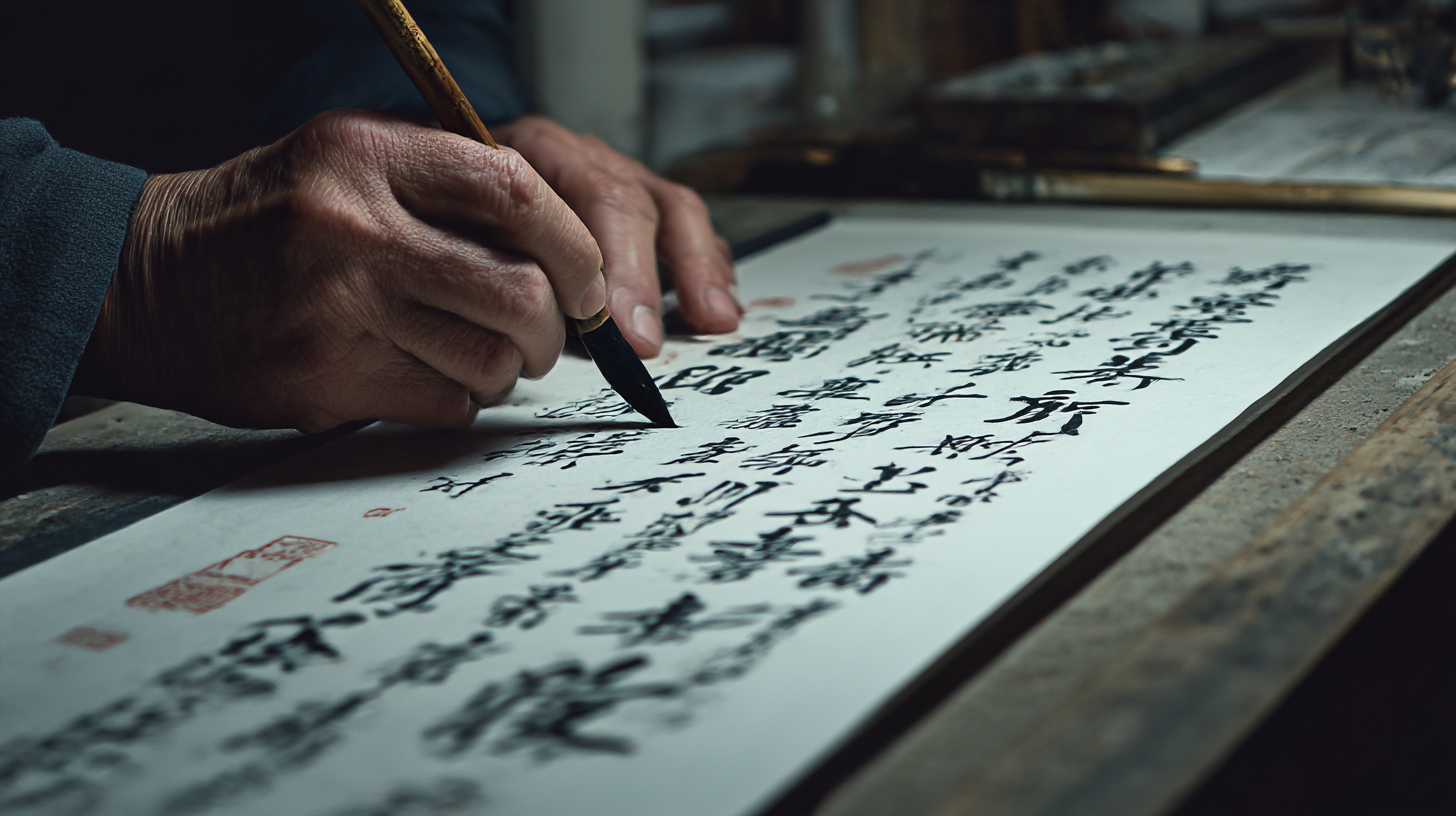
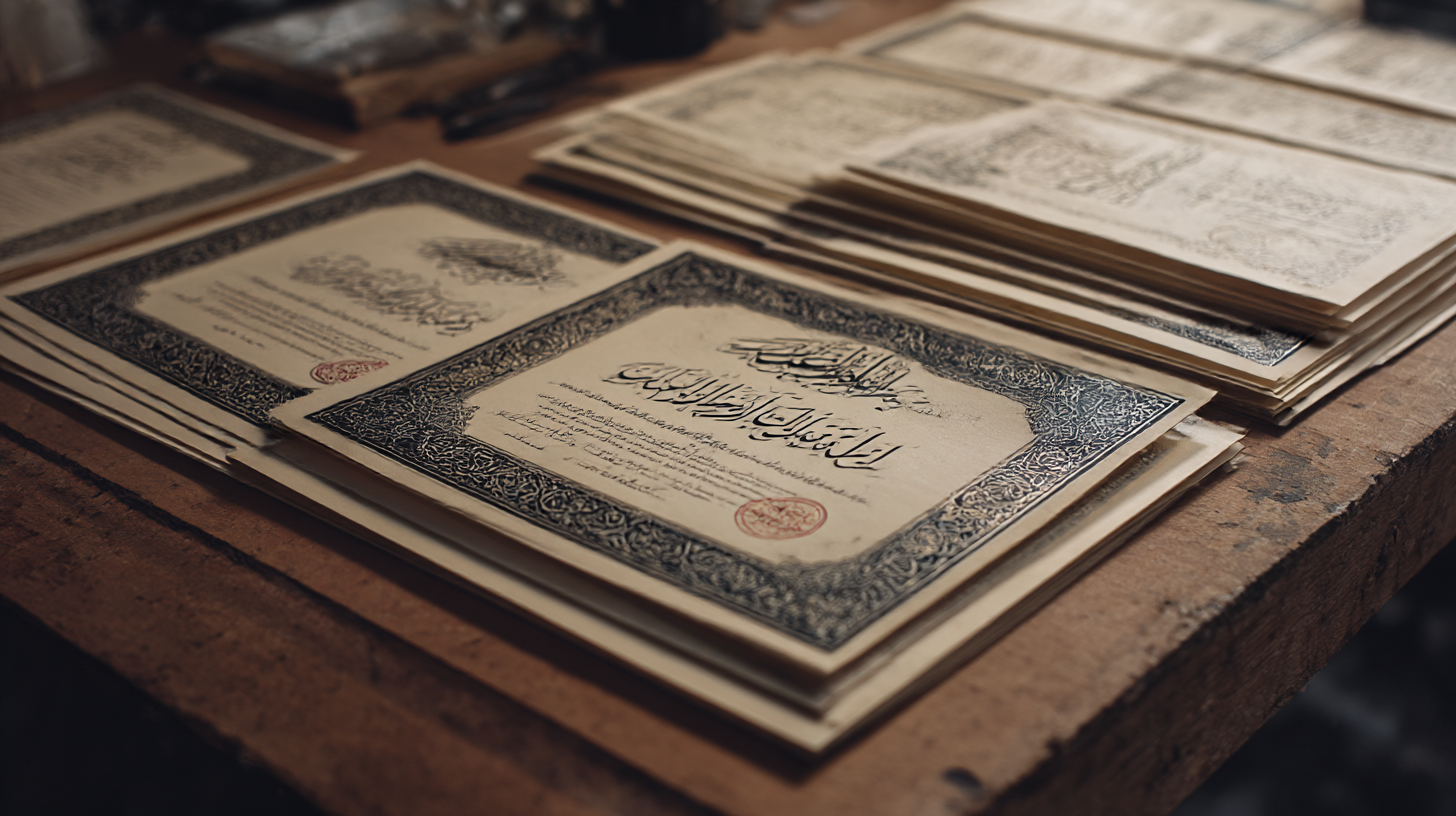
캘리그라피 자격증, 부업으로 연결되는 길 캘리그라피는 손글씨에 감성을 입히는 예술로, 단순한 취미에서 부업으로 연결될 수 있는 매력적인 분야예요. 예쁜 글씨체만 익히면 되는 게 아니라 감정과 메시지를 담아내는 표현력도 중요하죠.
이제는 캘리그라피 자격증을 통해 전문성을 인증받고, 그 실력을 바탕으로 다양한 활동을 펼칠 수 있어요. 저는 이 글을 통해 캘리그라피가 단순한 '글씨'를 넘어서 삶의 기회를 열어주는 열쇠가 될 수 있다는 걸 소개해보려고 해요.
🖌 캘리그라피란 무엇일까?
캘리그라피는 단순히 글씨를 예쁘게 쓰는 것이 아니에요. 감정을 담은 손글씨를 통해 사람의 마음을 움직이는 예술이랍니다. 손끝으로 전해지는 감정과 메시지는 활자나 디지털 폰트로는 느낄 수 없는 깊은 울림을 줘요. 특히 요즘처럼 감성이 중요한 시대엔 손글씨 하나로 감동을 줄 수 있답니다.
전통적인 서예와는 달리 캘리그라피는 자유롭고 창의적인 표현을 중요시해요. 굵기, 간격, 흐름 등 글씨의 형태를 통해 감정을 전달할 수 있기 때문에 아트워크로도 높은 평가를 받고 있어요. 특히 한국에서는 한글의 곡선미가 돋보이는 작품들이 인기를 끌고 있어요.
디지털 시대에도 캘리그라피는 꾸준히 주목받고 있어요. 감성적인 광고 문구나 SNS 콘텐츠에 자주 활용되며, 개성 있는 브랜드 아이덴티티를 만드는 데도 필수적인 요소로 자리 잡고 있어요. 손글씨 특유의 인간적인 매력이 사람들에게 따뜻함을 전달해주기 때문이에요.
요즘은 캘리그라피를 단순한 취미를 넘어서 직업으로 삼는 사람들도 많아졌어요. 결혼식 청첩장, 기업 광고, 유튜브 썸네일, 카페 메뉴판 등 다양한 분야에서 캘리그라퍼의 손길이 필요하답니다. 이처럼 수요가 점점 확대되면서 자격증을 취득해 전문성을 갖추려는 사람들이 늘고 있어요.
🖋 캘리그라피 스타일 비교표
스타일 특징 적용 예시 모던 캘리 자유로운 구조, 부드러운 곡선 SNS 게시물, 엽서 클래식 캘리 정형화된 서체, 균형감 강조 공식 문서, 전시 작품 일러스트 캘리 그림과 함께 감성 표현 굿즈, 캘린더 디자인 붓글씨 캘리 붓 특유의 강약 조절 전통 행사, 예술 전시 내가 생각했을 때 캘리그라피는 내면의 감성을 밖으로 표현하는 가장 따뜻한 방식 중 하나인 것 같아요. 글씨 하나하나에 마음이 실리기 때문에 보는 사람도 자연스럽게 공감하게 되거든요. 그리고 이게 바로 캘리그라피의 진짜 매력이 아닐까 싶어요. 😊
📚 자격증 종류와 취득 과정
캘리그라피 자격증은 다양한 기관에서 발급하고 있어요. 가장 많이 알려진 자격증은 '한국캘리그라피디자인협회', '한국실용글씨협회' 등의 민간자격증이랍니다. 이 자격증들은 공인된 국가자격은 아니지만, 실무 현장에서는 널리 인정받고 있어요. 실력을 기반으로 검정에 응시할 수 있고, 창작 능력도 함께 평가돼요.
보통 2급부터 시작해서 1급, 강사 자격까지 단계적으로 올라갈 수 있어요. 2급은 비교적 진입 장벽이 낮기 때문에 초보자도 부담 없이 도전할 수 있어요. 자격증 취득을 위해선 일정 기간 교육을 이수한 후, 실기 및 이론 시험에 통과해야 해요. 시험은 직접 글씨를 쓰는 방식으로 진행되며, 디자인 구성력도 중요한 요소랍니다.
자격증 교육 과정은 보통 온라인 강의나 오프라인 학원에서 받을 수 있어요. 특히 요즘은 온라인으로도 충분히 실력을 키울 수 있어서 직장인이나 육아 중인 분들에게도 접근성이 좋아요. 실시간 피드백이 가능한 커뮤니티도 많아서 피드백을 통해 빠르게 실력이 느는 경우도 많답니다.
자격증을 따면 끝이 아니라 시작이에요. 이후에는 포트폴리오를 준비하고 실제 작업 의뢰를 받아보는 경험이 중요해요. 자격증은 실력을 보여주는 수단이지만, 진짜 경쟁력은 '나만의 스타일'을 얼마나 잘 표현하느냐에 달려 있어요. 자격증은 실력을 증명하는 '티켓'일 뿐, 결국 실전 경험이 실력을 탄탄하게 만들어줘요.
📄 자격증 종류 비교표
자격증명 발급 기관 자격 구분 취득 난이도 특징 캘리그라피 2급 한국캘리그라피디자인협회 민간자격 ★★☆☆☆ 초보자용, 입문 단계 캘리그라피 1급 한국실용글씨협회 민간자격 ★★★☆☆ 실무 활용 능력 요구 캘리그라피 강사 자격 한국캘리그라피교육원 민간자격 ★★★★☆ 교육 강의 가능 캘리그라피 마스터 디자인연합협회 민간자격 ★★★★★ 작품 창작 및 심사 가능 위 자격증 중 어떤 걸 선택하느냐는 본인의 목적에 따라 달라져요. 취미로 즐기고 싶다면 2급이나 1급 정도가 적당하고, 교육이나 강사 활동을 고려한다면 강사 자격 이상을 목표로 하는 게 좋아요. 강의를 하고 싶은 분은 해당 교육기관의 커리큘럼을 꼼꼼히 비교해보는 게 중요해요.
💼 취미에서 부업으로 발전하기
캘리그라피는 단순히 여가 시간을 보내는 취미로 시작되기 쉽지만, 조금만 방향을 바꾸면 부업으로 연결되기 딱 좋아요. 내가 만든 손글씨 작품을 누군가가 돈 주고 구매한다는 건 정말 뿌듯한 일이죠. 무엇보다 온라인 플랫폼 덕분에 누구나 작품을 세상에 보여줄 수 있게 되었어요.
요즘은 SNS만 잘 운영해도 캘리그라피로 수익을 낼 수 있는 기회가 많아졌어요. 인스타그램, 블로그, 유튜브, 스마트스토어 등을 통해 작품을 판매하거나 강의를 열 수 있답니다. 자신만의 개성이 담긴 글씨와 표현 방식으로 팔로워들의 공감을 얻으면 브랜드 협찬이나 주문 의뢰도 자연스럽게 들어오게 돼요.
특히 수공예 마켓이나 온라인 클래스를 통해 상품을 판매하면 부업으로 꽤 괜찮은 수입을 만들 수 있어요. 청첩장 디자인, 감성 엽서, 포스터, 소품 제작 등 캘리그라피가 들어가는 상품은 무궁무진하거든요. 직접 굿즈를 만들어 판매하는 ‘작가 마켓’은 창작자에게 꿈같은 기회예요.
회사원, 주부, 프리랜서 누구든지 캘리그라피는 부업이 될 수 있어요. 하루에 1~2시간만 투자해도 실력을 쌓을 수 있고, 시간 제약 없이 운영할 수 있어서 본업과 병행하기에도 적합하답니다. 게다가 요즘은 ‘감성 소비’를 좋아하는 사람들이 많아서 손글씨만으로도 충분한 경쟁력이 생겨요.
💡 캘리그라피 부업 방법 비교표
부업 유형 특징 수익 구조 시작 난이도 굿즈 제작 판매 감성 제품으로 인기 제품 판매 수익 ★★★☆☆ 온라인 클래스 운영 꾸준한 수입 가능 강의 수강료 ★★★★☆ 청첩장/로고 제작 맞춤형 작업 의뢰비 수익 ★★★☆☆ SNS 콜라보 팔로워 수 기반 광고 협찬, 제휴 ★★☆☆☆ 캘리그라피는 정해진 형식이 없기 때문에 표현의 자유가 커요. 내가 어떤 문구를 어떤 스타일로 전달할지에 따라 전혀 다른 결과물이 나오니까 창의력이 발휘되는 부업이에요. 누구나 시작할 수 있지만, 내 감성을 담아내는 데 집중하면 진짜 '내 일'이 되는 순간이 찾아와요.
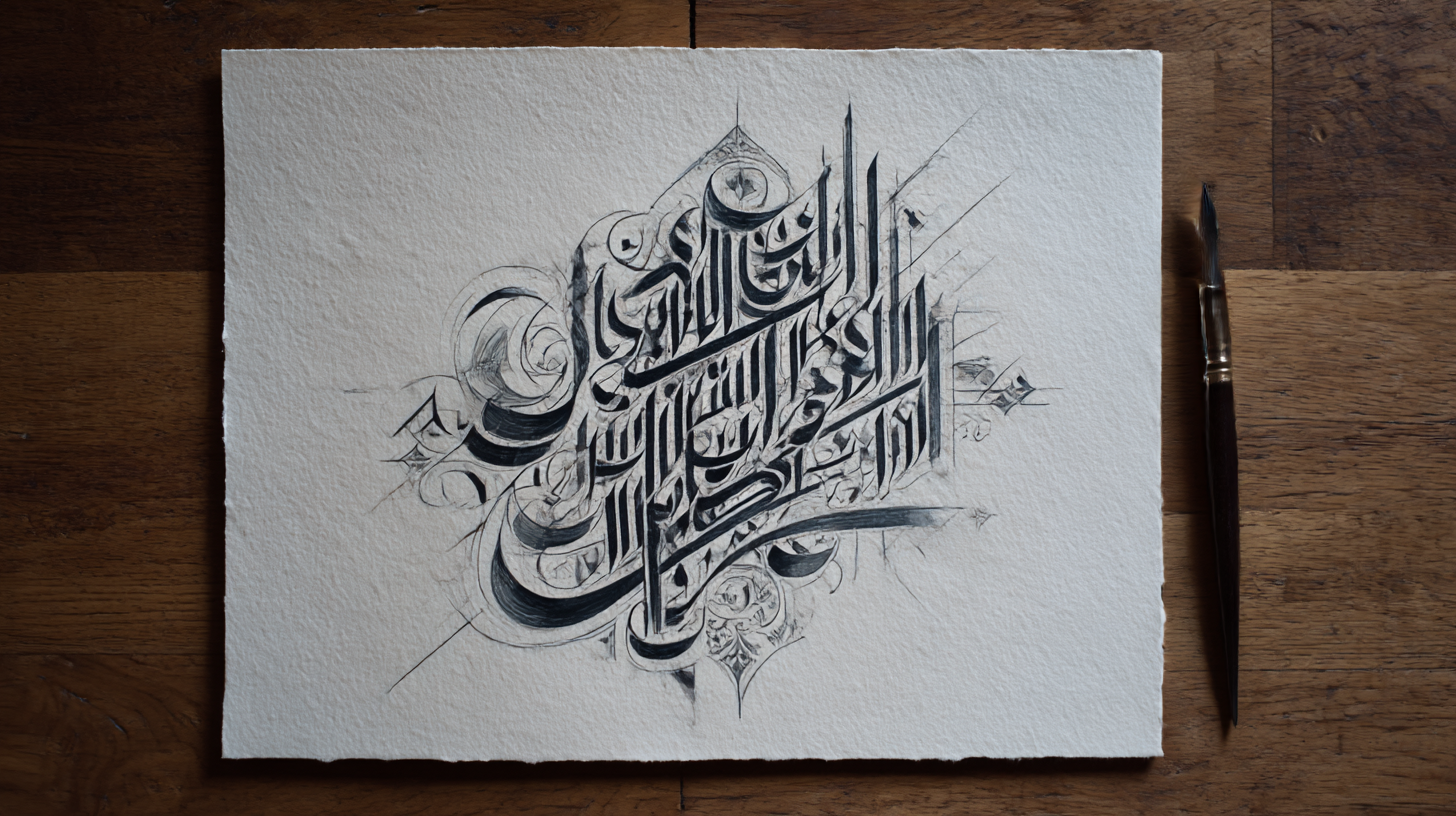
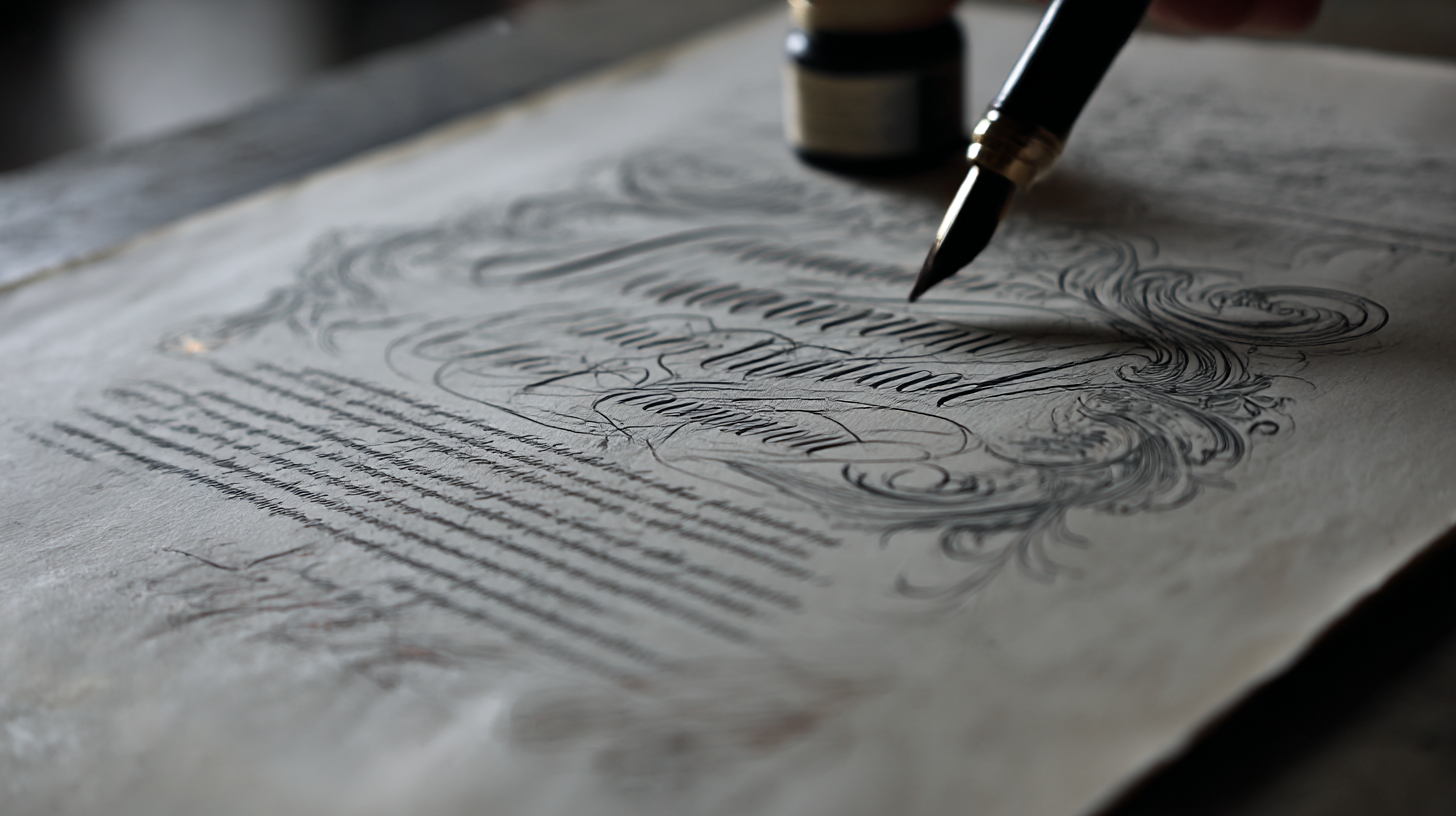
취미에서 부업으로 발전하기 💰 수익 창출 가능한 캘리그라피 분야
캘리그라피로 수익을 만들 수 있는 분야는 생각보다 훨씬 다양해요. 단순히 글씨 쓰는 활동을 넘어서 디자인과 콘텐츠가 결합된 영역이 많아졌기 때문이죠. 특히 '감성'이라는 키워드가 중요해진 요즘, 손글씨는 브랜드와 사람을 이어주는 중요한 매체로 주목받고 있어요.
첫 번째로 인기 있는 분야는 바로 ‘굿즈 제작’이에요. 손글씨로 만든 문구를 엽서, 포스터, 다이어리, 탁상달력 등에 적용해 판매하는 방식이죠. ‘오늘의 문장’, ‘마음 위로 엽서’ 같은 주제로 많은 사람들이 감동받고 구매해요. 공방이나 온라인 마켓, SNS를 통해 직접 판매할 수도 있어요.
두 번째는 ‘청첩장·감사카드 디자인’이에요. 결혼, 돌잔치, 개업 등 특별한 날을 기념하는 문구에 손글씨를 요청하는 사람들이 많아요. 정해진 글씨보다 개성 있고 따뜻한 느낌을 줄 수 있어서 많은 신랑신부, 행사 주최자들이 캘리그라피를 선택해요. 이 분야는 한 건당 단가가 높아 수익률이 좋아요.
세 번째는 ‘로고 및 브랜딩 디자인’이에요. 작은 브랜드, 카페, 독립서점 등에서는 감성적인 이미지를 위해 손글씨 로고를 선호하거든요. 특히 브랜딩 초기에 캘리그라피로 로고를 만든다면 따뜻한 이미지와 신뢰를 함께 줄 수 있어요. 실제로 유명 카페나 화장품 브랜드도 손글씨 로고를 활용해요.
📊 수익화 가능한 캘리그라피 분야 정리
분야 활동 예시 수익 유형 소요 시간 굿즈 제작 엽서, 달력, 포스터 판매 수익 중간 청첩장·카드 감사 인사, 초대장 주문 제작 수익 짧음 로고 디자인 브랜드 로고, 간판 디자인 수익 김 SNS 콘텐츠 감성 문구 이미지 협찬/광고 짧음 그 외에도 강연이나 워크숍, 기업 대상 출강, 클래스101 같은 온라인 플랫폼에서 수업을 열 수도 있어요. 잘 알려진 플랫폼에 입점하면 매달 정기 수입이 생기기도 해요. 이처럼 ‘감성’과 ‘글씨’가 중심이 되는 시장은 계속해서 확장 중이랍니다.
곧 이어질 섹션에서는 내 실력을 어떻게 사람들에게 보여줄 수 있을지, 효과적인 포트폴리오 제작과 SNS 운영법에 대해 알려줄게요. 이제 진짜 실전 감각을 키울 시간이에요! ✨
📷 포트폴리오와 SNS 활용법
캘리그라피를 부업으로 이어가려면, 내 실력을 효과적으로 보여줄 수 있는 '포트폴리오'가 필요해요. 단순히 잘 쓴 글씨를 나열하는 게 아니라, 나만의 스타일과 감성을 담아 사람들의 감정을 자극하는 것이 중요하죠. 시선을 사로잡는 작품 구성은 기본이에요.
좋은 포트폴리오란 단순히 사진 몇 장을 나열하는 게 아니에요. 예를 들어, "봄 감성 시리즈", "결혼 축하 문구", "카페 메뉴보드"처럼 주제별로 카테고리를 나눠 정리하면 훨씬 보기 좋아요. 작업 과정을 함께 보여주는 것도 신뢰감을 높이는 방법이에요. 손글씨가 완성되기까지의 흐름을 보여주면 보는 사람의 이해도도 높아져요.
Q4. 어떤 도구로 시작하는 게 좋을까요?
A4. 초보자는 붓펜이나 파브리아노 종이 같은 기본 도구로 연습하면 좋아요. 익숙해지면 붓이나 다양한 재질의 종이도 도전해볼 수 있어요.
Q5. 아이패드로 캘리그라피 가능할까요?
A5. 물론이에요! 아이패드와 애플펜슬, 프로크리에이트 앱 조합은 디지털 캘리그라피에 최적화돼 있어요. 수정이 쉽고 작업 시간도 줄일 수 있어요.
Q8. 초보자가 가장 먼저 해야 할 일은 뭔가요?
A8. 자격증 취득 여부와 상관없이 나만의 문구 스타일을 찾고 꾸준히 연습하는 게 가장 중요해요. 나만의 감성 글씨를 만들어가는 게 출발점이에요!